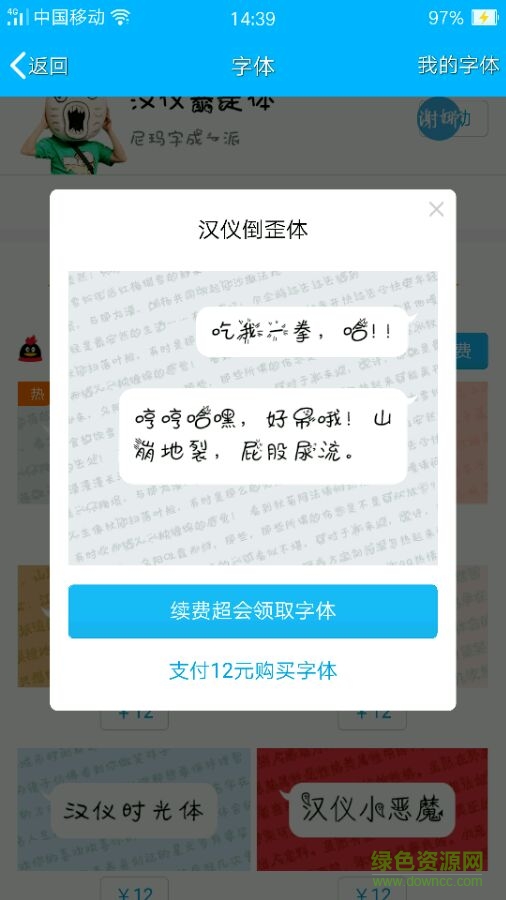
漢儀倒歪字體在眾多字體中風格十分獨特,是一款備受矚目的漢儀字體,能夠讓人一眼即可愛不釋手,運用到多種媒體制作當中,擁有十分顯眼的顯示效果,同時能夠為你的作品增添出別樣的風采!快來綠色資源網(wǎng)下載吧!
漢儀倒歪體字體展示小編點評
漢儀倒歪體在使用的過程中一度讓我欣喜異常,眾多好友都跟我求這個字體,真的是太好看了!
漢儀倒歪體
漢儀倒歪體字體介紹